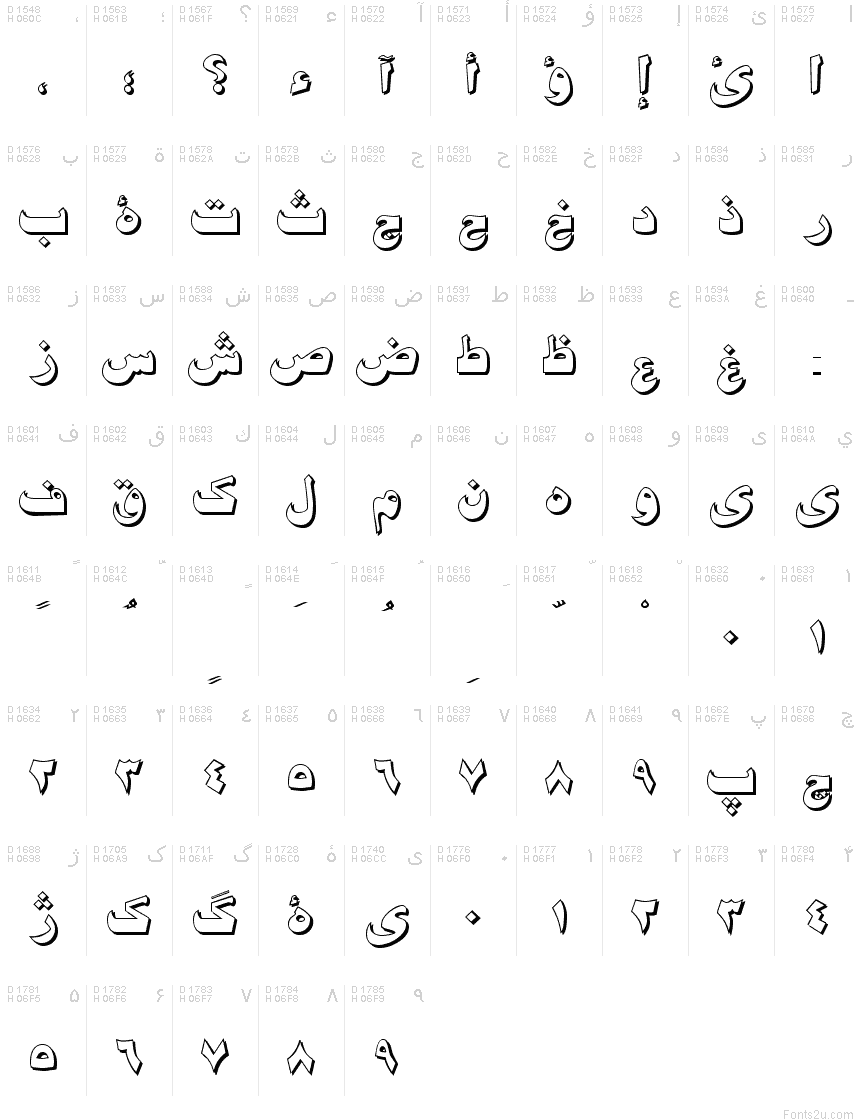
B Majid Shadow, un font arabo gratuito di tipo display di Borna Rayaneh, si distingue per un carattere audace da titolo, con la profondità integrata direttamente nelle lettere. Le forme appaiono ampie e incisive, mentre l'effetto ombra conferisce al font un impatto da poster che colpisce più per il suo aspetto grafico che per quello calligrafico.
È ideale per il branding di packaging per prodotti alimentari mediorientali, flyer musicali, insegne, grafiche per festival e titoli, dove un font gratuito con profondità integrata riesce a dire di più con meno. Usalo per titoli arabi brevi, testi di copertina o lettering in stile logo che richiedono più spessore e teatralità, senza dover aggiungere effetti extra.